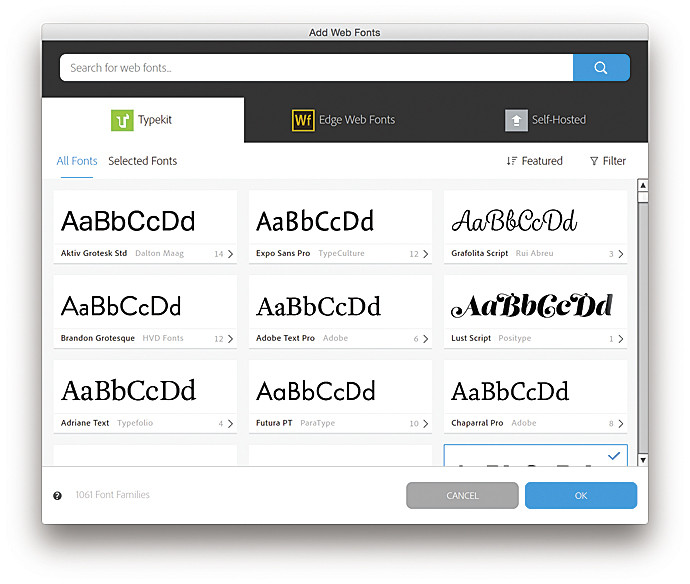
Самые популярные шрифты для сайта и web-дизайна
Несомненно, выбор шрифтового решения играет огромную роль в восприятии сайта. Ведь большинство сайтов состоит из текстов практически полностью.
Томас Лауринавичус (Tomas Laurinavicius) заинтересовался, какие шрифты любят больше всего использовать веб-дизайнеры в своей работе.
Он провел небольшое социологическое исследование для выявления самых популярных и любимых шрифтов среди создателей дизайна сайтов и блогов.
Кроме того, он взял короткое интервью у веб-дизайнеров с целью узнать, какой шрифт наиболее подходит в определенной ситуации. Результатами своего опроса Томас поделился на сайте hongkiat.com.
Опрос проводился в социальных сетях и микроблогах – Polldaddy, Forrst, Facebook и Twitter. В опросе приняли участие 34 дизайнера из 14 стран, которые, отвечая на вопросы о любимых шрифтах, объяснили, почему выбирают именно их._(9507).jpg)
Во время опроса веб-дизайнеры назвали 73 различных шрифта – 46 бесплатных и 27 платных.
Самыми любимыми шрифтами веб-дизайнеров оказались: Helvetica, Arial, Georgia, Gotham, Myriad Pro, DIN, Futura, League Gotic, Cabin, Corbel.
Нужно учитывать, что не все из представленных шрифтов имеют кириллическое начертание – тем более, в бесплатном варианте.
Далее показано два топ-10 – самые любимые бесплатные и платные шрифты.
Топ-10 любимых бесплатных шрифтов веб-дизайнеров
Опрошенные дизайнеры выбрали 10 лучших шрифтов для веб-графики. При этом не учитывались шрифты, по умолчанию установленные в операционную систему, такие как, Arial, Verdana, Times New Roman, Georgia или Tahoma. (Это немного странно – на первом месте шрифт, который есть в операционной системе).
- Myriad Pro
- League Gothic
- Cabin
- Corbel
- Museo Slab
- Bebas Neue
- Ubuntu
- Lobster
- Franchise
- PT Serif
Топ-10 любимых платных шрифтов веб-дизайнеров
В следующем списке самые популярные платные шрифты, используемые в веб-графике и дизайне.
Некоторые из них очень дорогие, но их качество говорит само за себя и оправдывает затраты.
- Helvetica
- Gotham
- DIN
- Futura
- Neo Sans
- Adobe Caslon
- Skolar
- Kautiva
- Caecilia
- Fedra Sans
Разработка web сайтов, шрифты для web
Всем привет! Сегодня в рамках рубрики о веб-дизайне хочу рассказать, о шрифтах которые следует использовать при разработке web сайта.
Как правило, не все задумываются о том, какие следует использовать шрифты для контентной части сайта. Подбор красивых шрифтов для сайта является наиважнейшей частью разработки дизайна.
Так как от этой части зависит читаемость информации сайта, а это, как известно самое главное на сайте. По этой причине к этому вопросу стоит отнестись весьма серьезно.
Но использовать в дизайне сайта можно только те шрифты, которые есть у будущих посетителей сайта. Это делается для того чтобы страницы отображались корректно у Всех пользователей, с разными операционными системами и браузерами. В противном случае если использовать не стандартные шрифты, то большинство посетителей увидит все по-разному и в большинстве случаев в неприглядном виде. По этой причине рекомендуется использовать стандартные шрифты, которые приведены ниже в списке. В список шрифтов входят шрифты, которые установлены на операционной системе Windows XP и выше.
В данной статье я не рассматриваю шрифты из других операционных систем. Опытный верстальщик, должен знать сопоставление шрифтов в различных операционных системах, и во время верстки он пропишет этот момент в css-стилях.
В основном разрабатывая контентную часть дизайна используются две разновидности шрифтов:
- шрифты с засечками
- рубленые шрифты (шрифты без засечек)
Шрифты с засечками — (англ.
serif — засечка) шрифты начертание которых начинается и заканчивается штрихами. Например Times New Roman.
Шрифты без засечек (рубленые шрифты) — (англ.sans-serif —без засечки) шрифты со строгими ровными линиями без засечек. Например Arial.
Ниже Вы можете увидеть скриншот шрифтов с засечкой и без.
Шрифты для web дизайна:
- Arial
- Arial Black
- Arial Narrow
- Book Antiqua
- Century Gothic
- Comic Sans MS
- Courier New
- Franklin Gothic Medium
- Georgia
- Impact
- Lucida Console
- Lucida Sans Unicode
- Microsoft Sans Serif
- Palatino Linotype
- Sylfaen
- Tahoma
- Times New Roman
- Trebuchet MS
- Verdana
- Webdings (различные символы и знаки)
- Wingdings (различные символы и знаки)
Также хочется заметить такой момент как отсутствие курсива у ряда шрифтов, вместо курсива в них используется наклон, из-за чего текст становится плохо читабельным.
эффект.Имя класса всегда начинается с font-effect- и заканчивается именем эффекта .
Пример
Добавить эффект огня к шрифту «София»:
Результат:
Попробуй сам » Чтобы запросить несколько эффектов шрифта, просто разделите имена эффектов вертикальной чертой
( | ), вот так:
Пример
Добавьте несколько эффектов к шрифту «Sofia»: